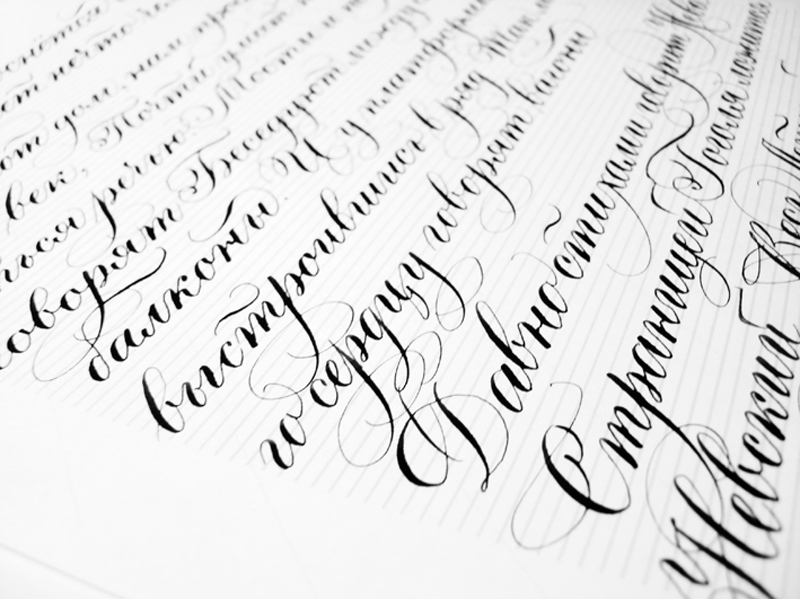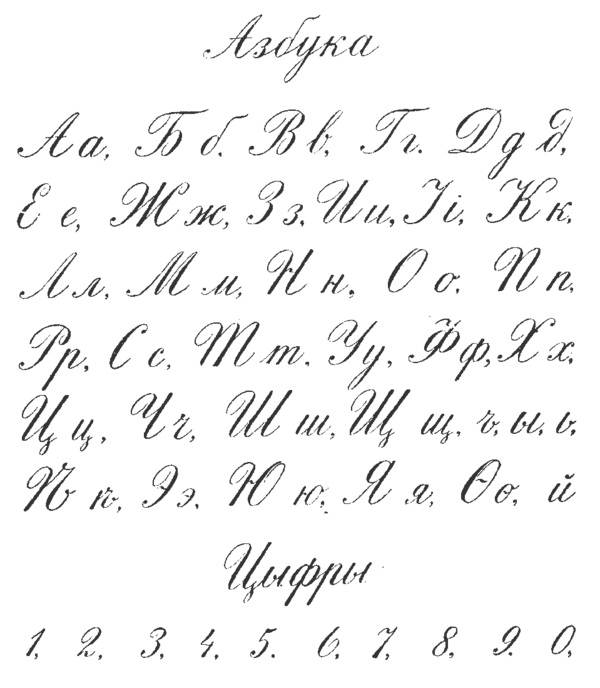
Рукописный шрифт
—
шрифт, литеры которого выглядят как буквы написанные от руки.
С помощью рукописных шрифтов имитируют надписи выполненные от руки различными пишущими инструментами — карандашом, ручкой, пером, кистью. Рукописные шрифты получили большое распространение в различных поздравлениях, приглашениях и оформлении надписей праздничных мероприятий.
Рукописные шрифты имеют и один недостаток, их труднее воспринимать визуально, а следовательно, читать большие тексты сложнее. Это следует учитывать при выборе начертания шрифта для оформления текста, поэтому рукописные шрифты следует использовать в заголовках, отдельных фразах и в небольших текстах, для придания строкам отдельного внимания и значимости. Для средних и больших текстов лучше использовать стандартные, легко читаемые шрифты, чтобы не утомлять читателя.
В нашем каталоге собрано множество рукописных русских шрифтов, каждый из которых отличается от других, своей неповторимостью.
Шрифты для письма ручкой. Рукописный шрифт для Word. Создадим тетрадный лист в клетку
На днях наша группа столкнулась с серьезнейшей проблемой — за пропуски пар надо сдать рефераты, написанные от руки. За два пропуска — 1 реферат на 15 листов! Да я за весь семестр столько бумаги не измарал, слава яйцам. Поэтому пришлось пойти на хитрости, а именно: найти нормальные (кириллические) и загнать их в Microsoft Word, и распечатать наши рефераты.
Сделать свой русский рукописный шрифт
Но, скачав эти шрифты, стало понятно, что никто не поверит, будто мы пишем, как Пушкин, Боярский или Моцарт. Поэтому пришлось сделать рукописный шрифт самим. Но как сделать свой шрифт, как две капли воды похожий на ваш обычный почерк?
Далее, на чистом листе (в линейку и в клетку не подойдут) пишем все буквы русского (английского, и других при необходимости) алфавита, а также цифры и спец. символы.
Следующий этап в Font Creator:
— Нажимаем файл — новый (New)
— Даем название своему рукописному шрифту (например Moy_shrift), ставим отметку на Unicode, на Regular и на Don’t include outlines (для чистого бланка силуэтов), короче, все по умолчанию.
- Если возможно, зафиксируйте поверхность бумаги на наклонной поверхности (вы можете использовать офисный пластилин (Blu Tack) и изоленту).
Если вы используете гусиное перо или перьевую ручку:
- Держите чернила / краску открытой и поставьте ее рядом с рукой, который вы не пишите.
- Выберите хорошее «место для стоянки», чтобы безопасно макать ручку, и избежать разбрызгивания чернил на другие поверхности. Вы можете взять небольшое блюдце, в котором будут размещаться ваши инструменты, в то время, как у вас будет перерыв или, если вы прерветесь на телефонный разговор.